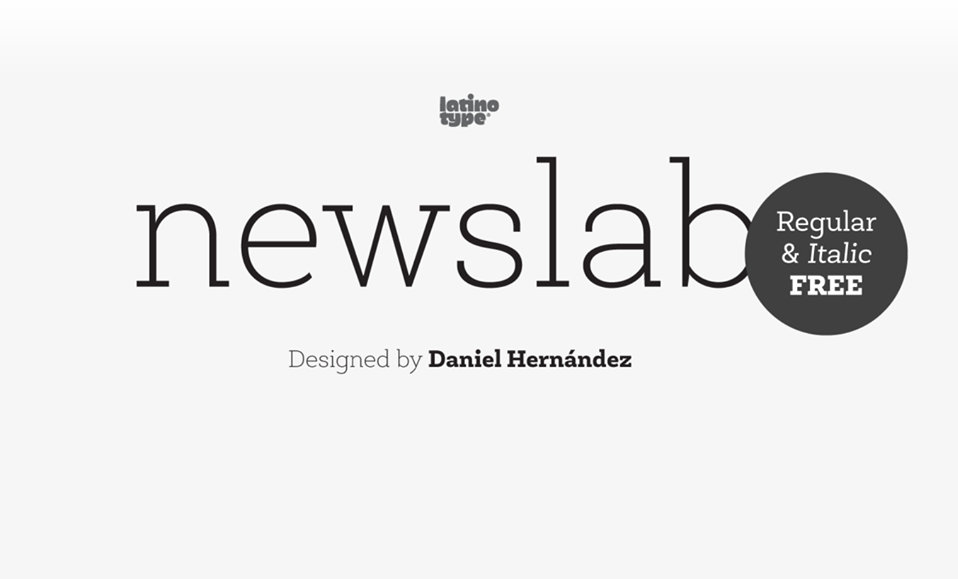
Newslab font family – Download Grátis
NovaLab é uma família de fontes serif que foi criada pela Hamilton. Fundida a partir de três tipos diferentes — Andes, Sánchez e Roble –, NovaLab resulta num estilo de fonte que evoca um equilíbrio harmonioso entre as diversas características das tipografias originais. Perfeitamente neutra e imponente ao mesmo tempo, NovaLab se destaca por sua forma sólida e robusta que promove uma leitura clara e profissional. A família de NovaLab traz consigo um conjunto versátil de fontes, capazes de adaptar-se a diversos usos, desde headlines até textos mais detalhados. Sua estrutura firme e sua paleta de cores sóbrias fazem dela uma escolha perfeita para aplicativos que exigem um toque de elegância e força no design.